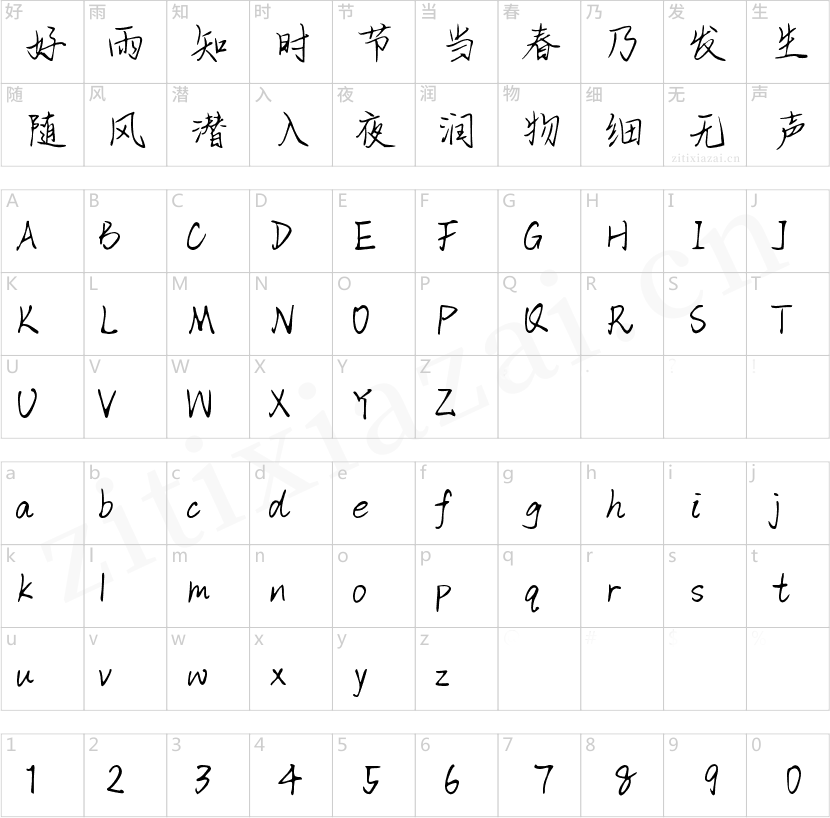
Aa醉眼望云烟
Aa醉眼望云烟字体
Aa醉眼望云烟是一款非常具有艺术性的字体,它的设计灵感来源于对古典艺术的研究,同时又融入了现代字体设计的元素。字形优美,笔画粗细变化自然,给人以大气、典雅的感觉。Aa醉眼望云烟是一款既传统又现代的字体,它的设计充满艺术感,美观大方,实用性也非常强。无论是对于设计师还是对于普通读者来说,都是一种非常不错的字体选择。Aa醉眼望云烟适合用于具有艺术感的场合,比如海报、宣传单张、书籍封面等。由于其字形流畅且具有动态感,也适合用于大量的文本排版,如报纸、杂志等。